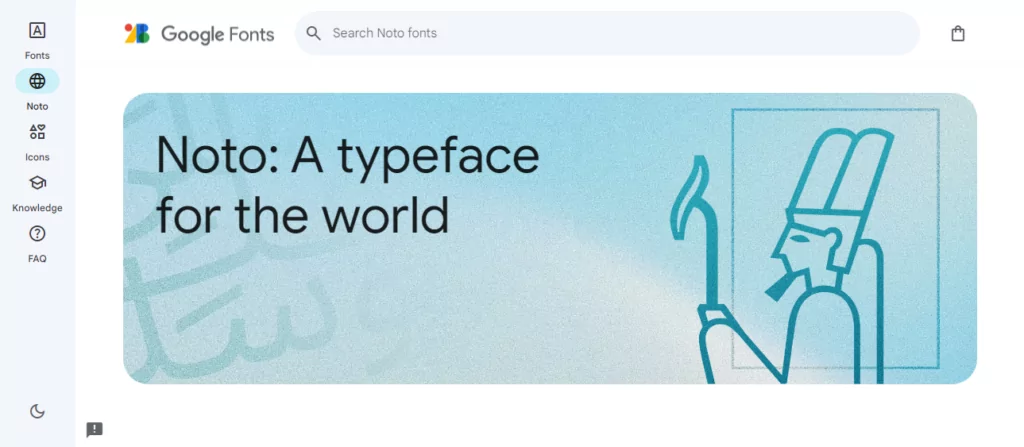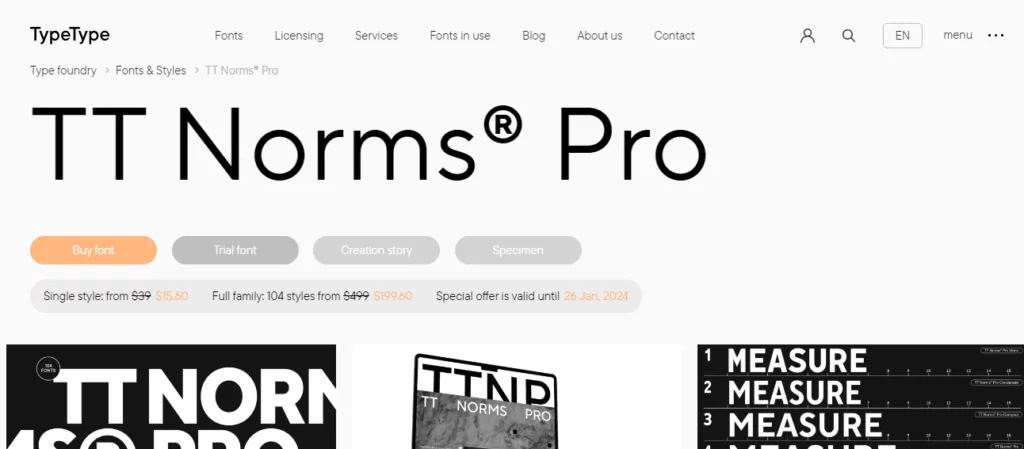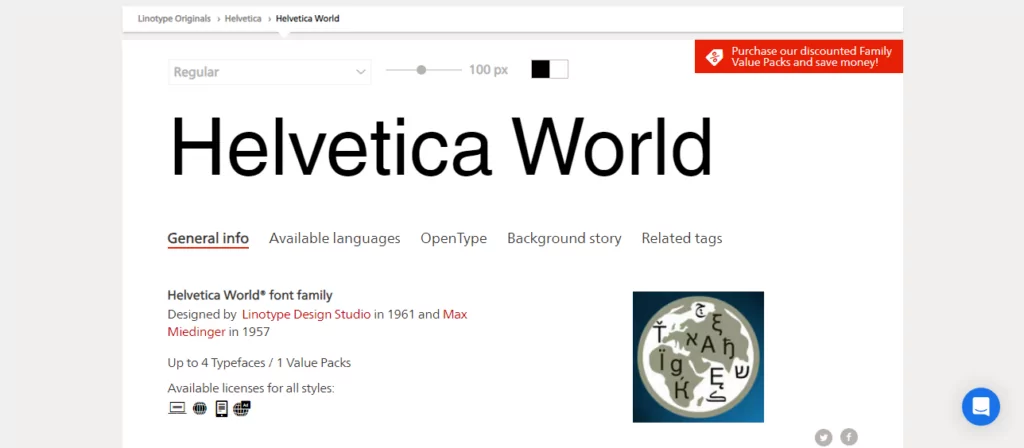
Cele mai bune fonturi multilingve pentru site-uri web în mai multe limbi
Publicat: 2023-12-14Sunteți în căutarea celor mai bune fonturi multilingve pentru site-ul dvs. în mai multe limbi? Dacă da, suntem atât de încântați că ați găsit acest articol.
Construirea unui site web multilingv este dificilă, mai ales dacă ești începător și faci asta singur. Devine mai dificil dacă designul web nu este punctul tău cel mai tare.
Vreau să spun. În crearea unui site web de succes în mai multe limbi sunt luate în considerare multe considerente. Ce serviciu de traducere ar trebui să utilizați? Care platformă este cea mai bună pentru un site web multilingv? Este traducerea umană mai bună decât traducerea automată? Și așa mai departe.
Un alt aspect critic este tipul de fonturi pe care le alegeți pentru site-ul dvs. multilingv.
De ce este acest lucru important? E simplu.
Unele fonturi arată grozav și sunt clare și lizibile într-o singură limbă. Cu toate acestea, același font ar putea să nu impresioneze atunci când este tradus într-o altă limbă.
Cu alte cuvinte. traducerile rezultate sunt peste tot, ilizibile și pline de simboluri dreptunghiulare verticale cunoscute în mod obișnuit sub numele de tofu.
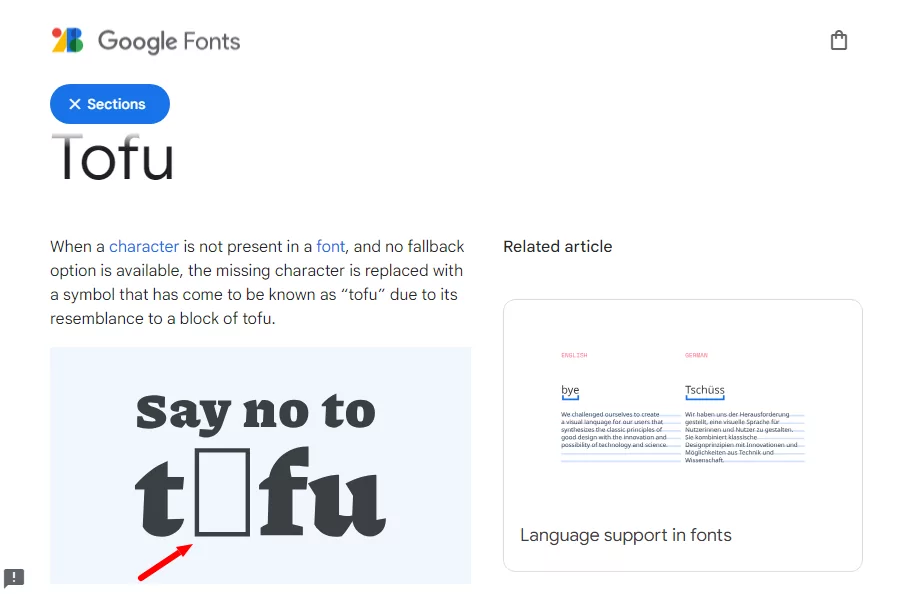
Sunt sigur că ați văzut unele dintre ele când ați vizitat un site web cu traduceri slabe. Și putem fi cu toții de acord că nu arată bine, mai ales când doriți să ajungeți la un public multilingv.
Ce sunt fonturile multilingve?
Fiecare limbă scrisă folosește diferite alfabete, seturi de caractere, convenții, semne diacritice, glife și scripturi. Din acest motiv, nu este înțelept să presupunem că tot conținutul tău va arăta grozav și va fi lizibil atunci când este tradus în diferite limbi.
Spun asta pentru că unele fonturi sunt destinate unei singure limbi. Adică fontul nu are setul de caractere de care aveți nevoie pentru traduceri de lucru în alte limbi.
Aici intervin fonturile multilingve pentru a salva ziua.
Spre deosebire de un font convențional care funcționează cu o singură limbă, fonturile multilingve sunt concepute pentru a accepta mai multe limbi.
Fă-ți timp și cercetează fonturile pe care le vei folosi, deoarece contează pentru experiența utilizatorului și eficacitatea conținutului tău.
Astăzi, explorăm de ce companiile folosesc fonturi multilingve, ce ar trebui să luați în considerare atunci când alegeți un font și apoi împărtășim mai multe favorite.
De ce ar trebui să utilizați fonturi multilingve
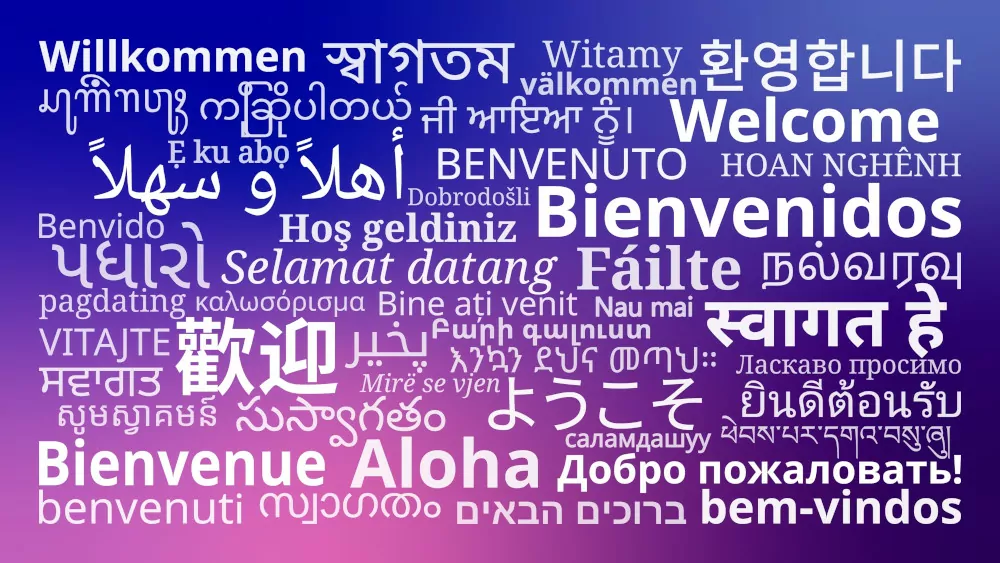
Dacă nu sunteți un dezvoltator web experimentat sau un designer de tipări, s-ar putea să vă întrebați de ce folosiți fonturi multilingve.
Ei bine, utilizarea fonturilor multilingve de încredere pe site-ul dvs. în mai multe limbi oferă mai multe beneficii. În afară de a fi una dintre cele mai bune practici de proiectare a site-urilor web multilingve, iată mai multe motive pentru care ar trebui să utilizați fonturi în mai multe limbi.
Lizibilitatea și lizibilitatea
Acesta este cel mai evident beneficiu al alegerii celor mai bune fonturi pentru mai multe limbi.
După cum am sugerat mai devreme, fiecare limbă are setul său unic de caractere, convenții, glife și scripturi, printre altele.
Ca o ilustrare, limbi precum arabă și chineză au caractere diferite decât engleza. Dacă fontul pe care îl alegeți îl acceptă doar pe cel din urmă, traducerile dvs. vor arăta groaznic în celelalte două limbi.
Pe de altă parte, utilizarea fonturilor multilingve asigură că caracterele traduse sunt afișate corect și nu sunt înlocuite cu simboluri generice, cum ar fi tofu.
Indiferent de modul în care doriți să-l vedeți, obiectivul dvs. general cu un site web multilingv este de a oferi conținut lizibil și lizibil publicului(e) indiferent de limbile lor preferate.
Preveniți problemele tulburătoare de afișare
Când traduceți un site web, probabil ați observat cum se mișcă lucrurile atunci când schimbați limbile.
Dacă rămâneți cu un font tipic, unele caractere dintr-o limbă nu vor fi disponibile în traduceri, ceea ce cauzează probleme de afișare.
Un font multilingv, pe de altă parte, vine cu o gamă largă de caractere, ceea ce asigură că conținutul tău arată atractiv în ciuda limbajului de traducere.
Vă recomandăm să utilizați un font multilingv la afișarea traducerilor pentru a evita un design care pare deconectat din cauza utilizării de fonturi diferite pentru fiecare limbă.
Această consecvență vă permite să creați o imagine de marcă rafinată și profesională în toate limbile.
Experiența utilizatorului îmbunătățită
Nu este un secret pentru nimeni că oferirea unei experiențe de utilizator superbă merge mână în mână cu o mai bună reținere a utilizatorilor, implicare și conversii.
Cu alte cuvinte, vizitatorii care accesează site-ul dvs. în mai multe limbi prin diferite limbi ar trebui să aibă cu toții o experiență plăcută și să se simtă confortabil cu designul site-ului dvs.
Fonturile multilingve vă ajută să stabiliți o experiență de utilizator plăcută, care le permite vizitatorilor să înțeleagă, să se bucure și să interacționeze cu conținutul site-ului dvs.
Concluzie
Încă nu vă puteți decide asupra fontului multilingv de care aveți nevoie pentru site-ul dvs. în mai multe limbi? Să-ți spun, e simplu. Începeți cu ceva sigur, cum ar fi Google Noto sau Open Sans, și mergeți de acolo.
După cum v-ați aștepta, veți avea nevoie de multă cercetare în prealabil pentru a găsi fontul perfect pentru site-ul dvs. multilingv.